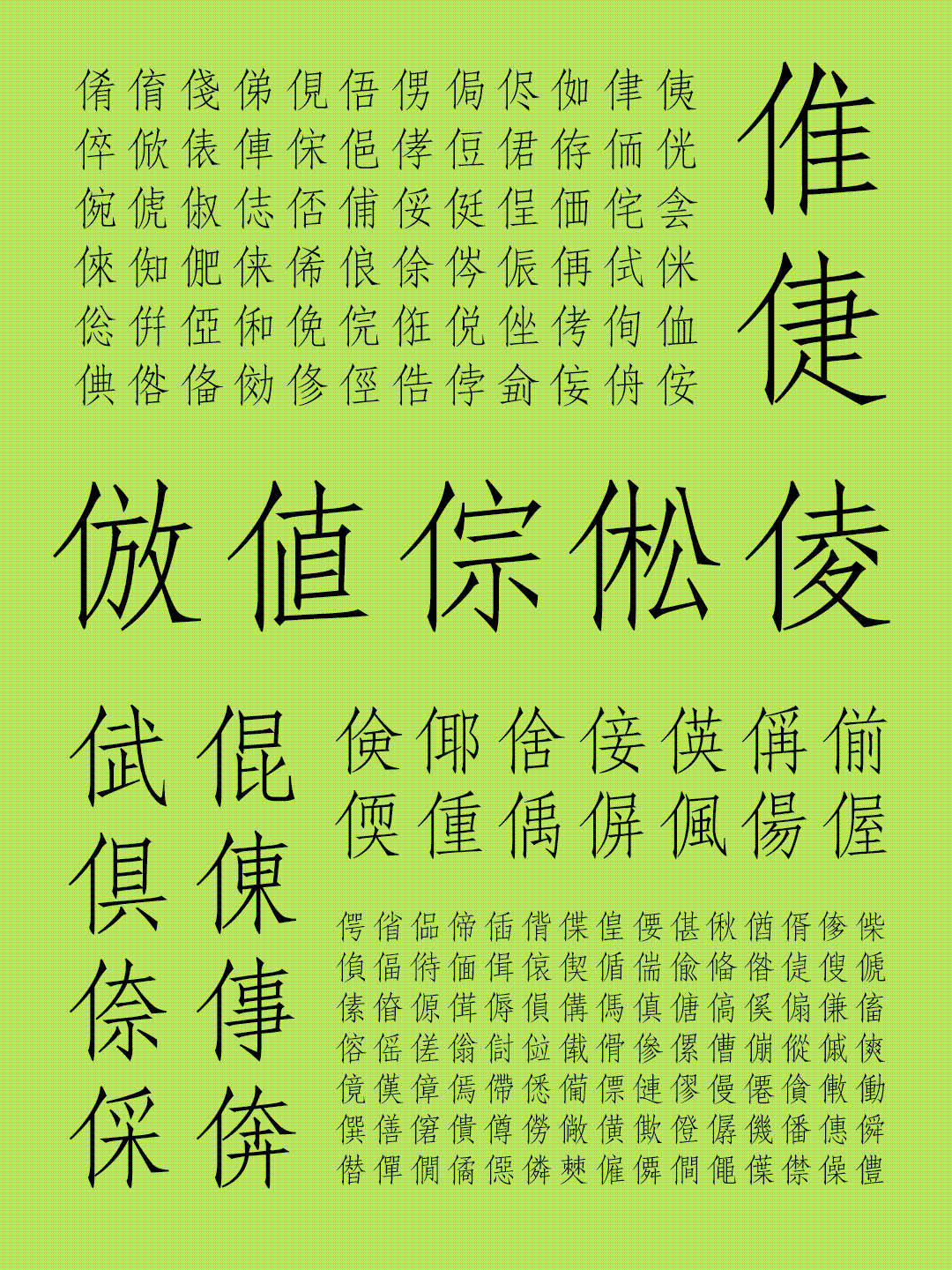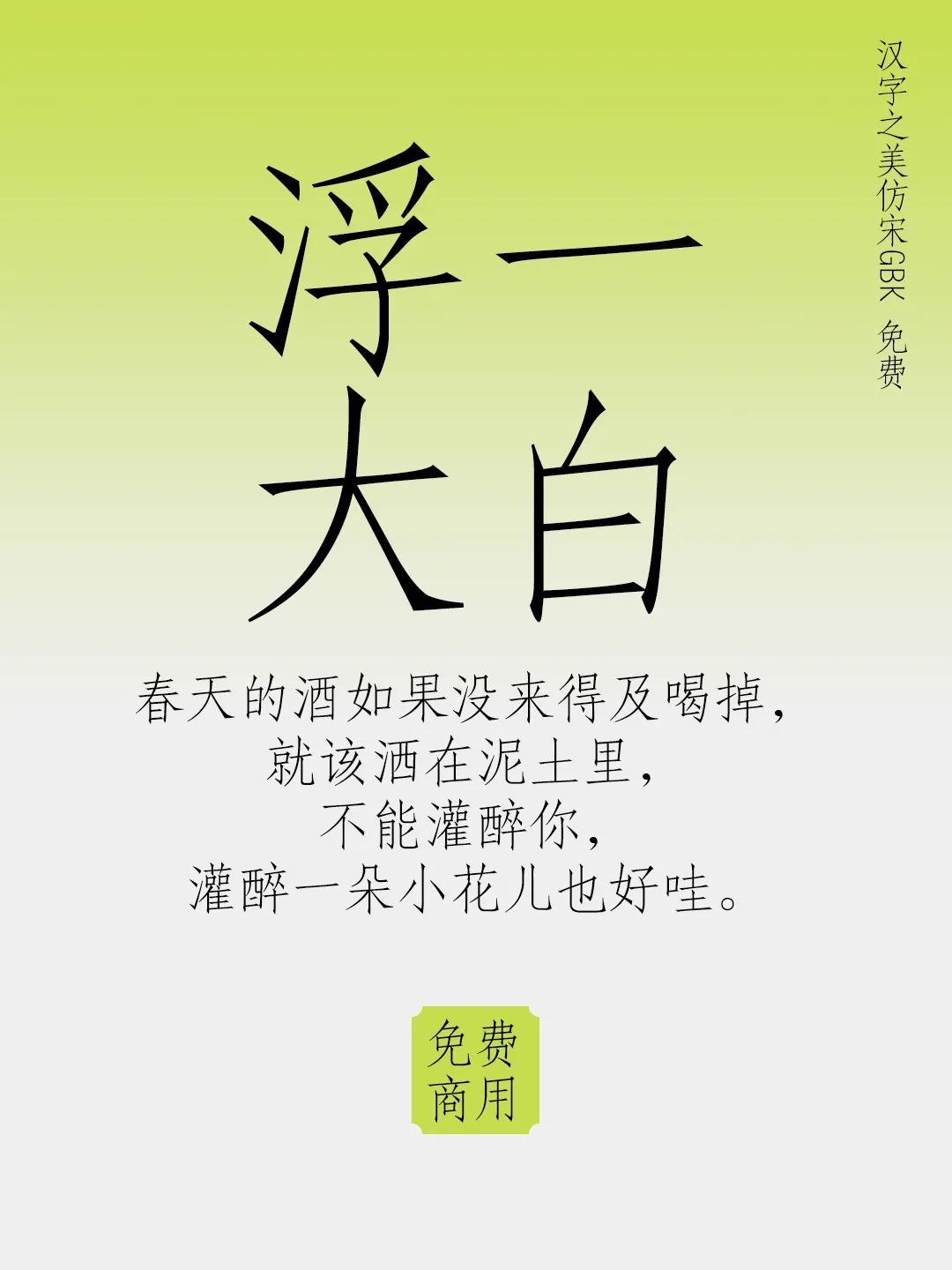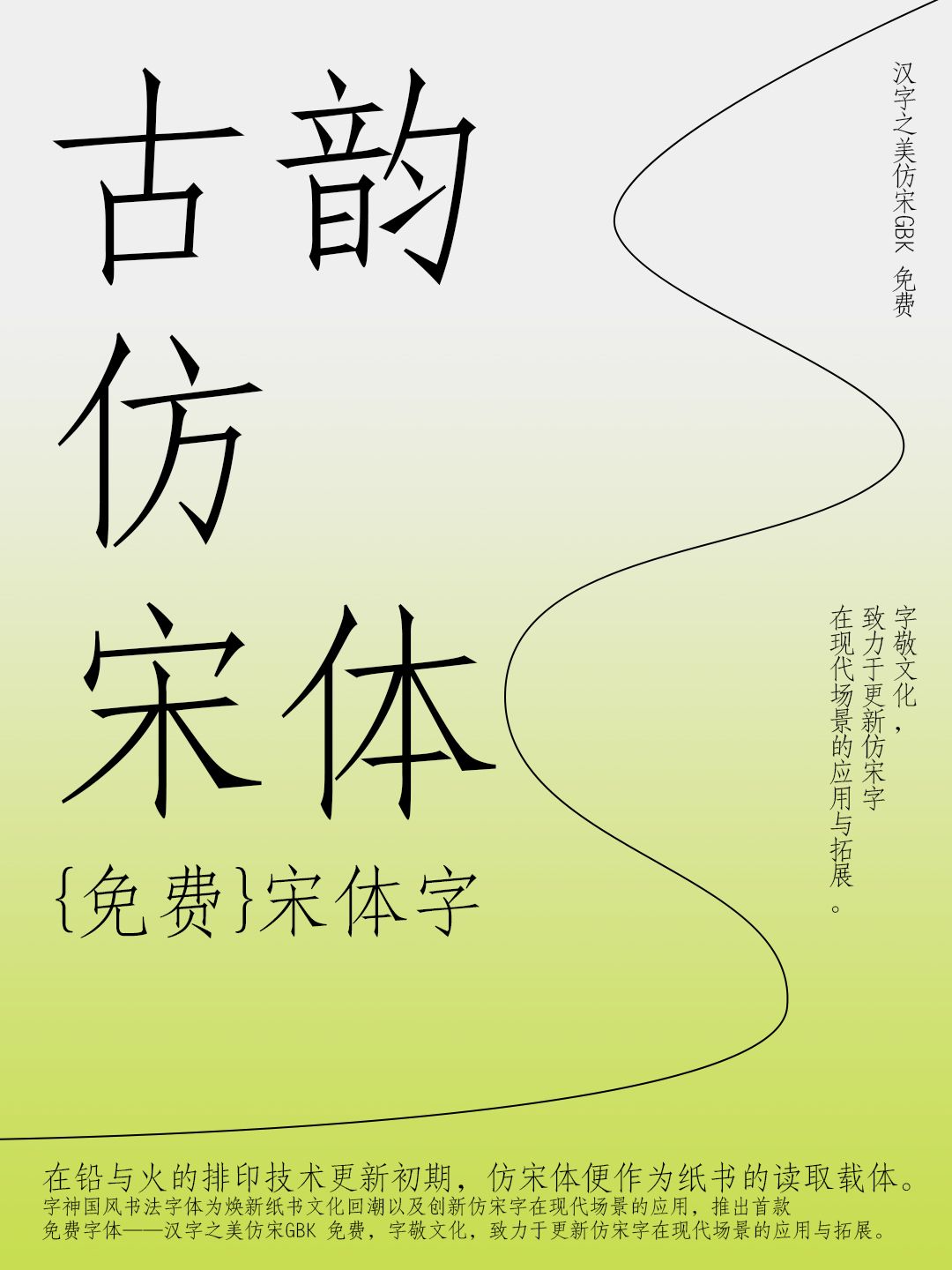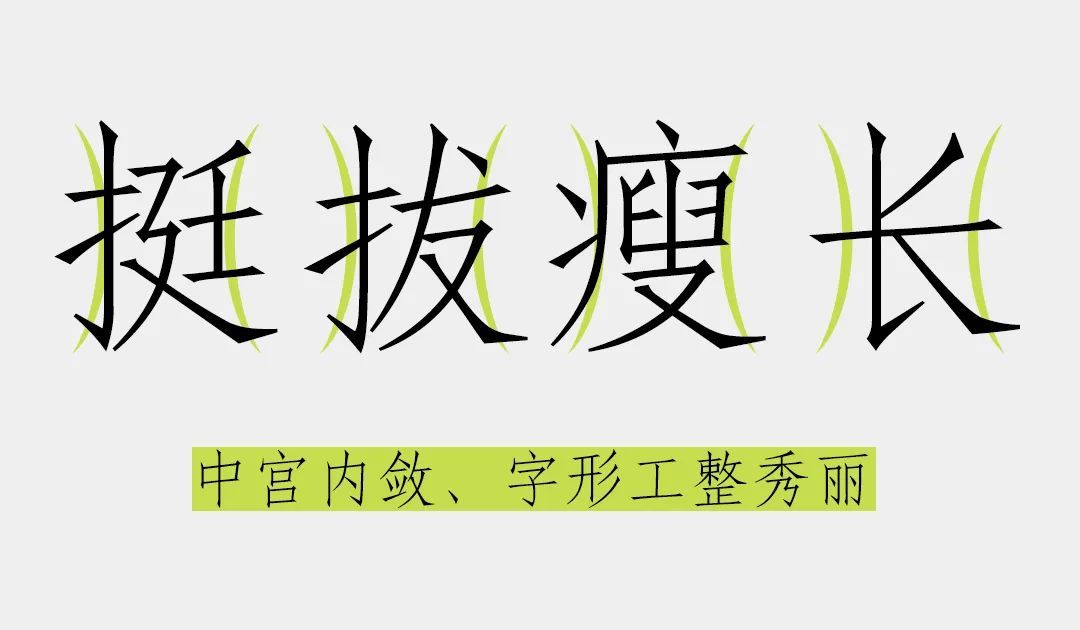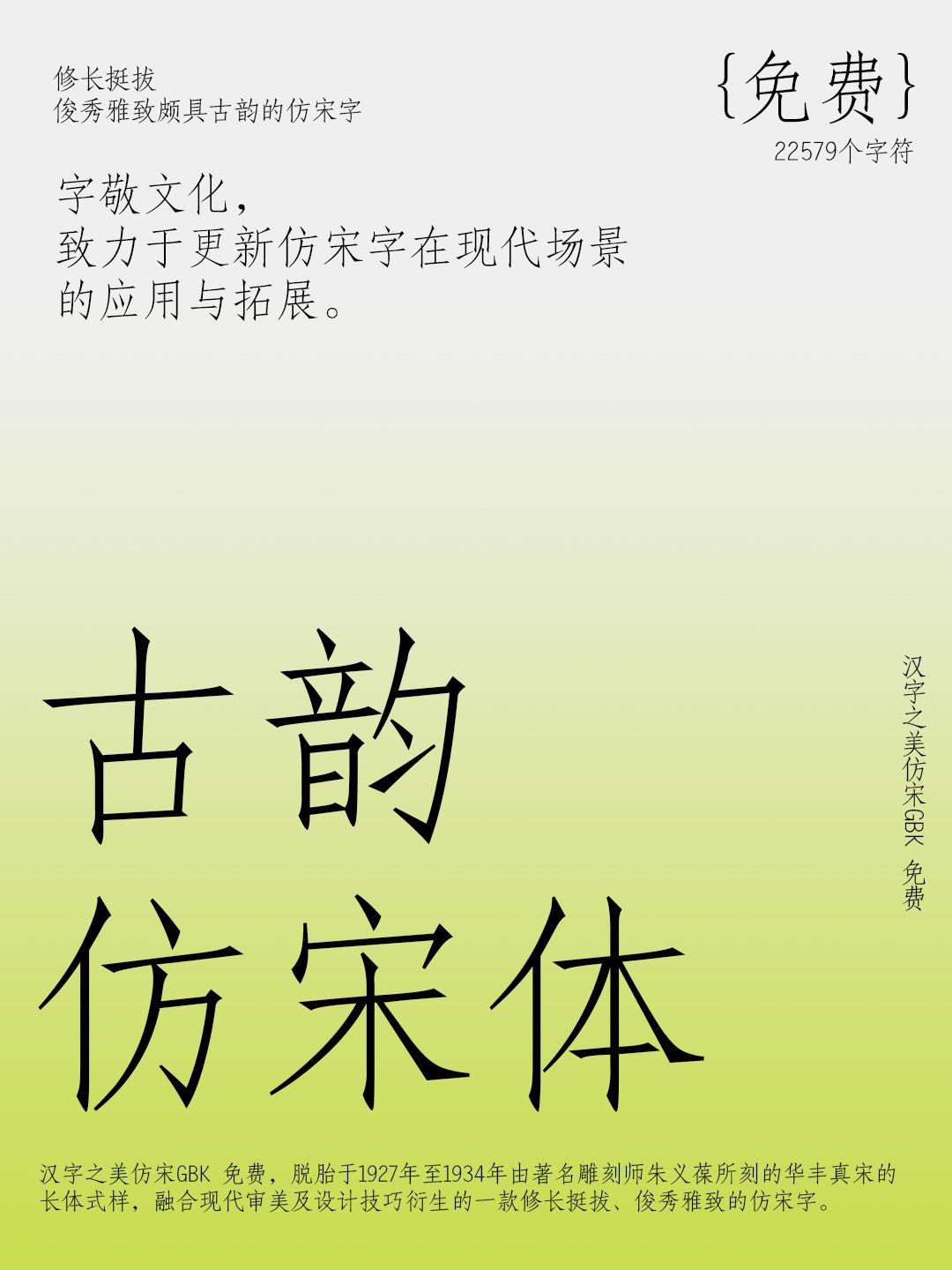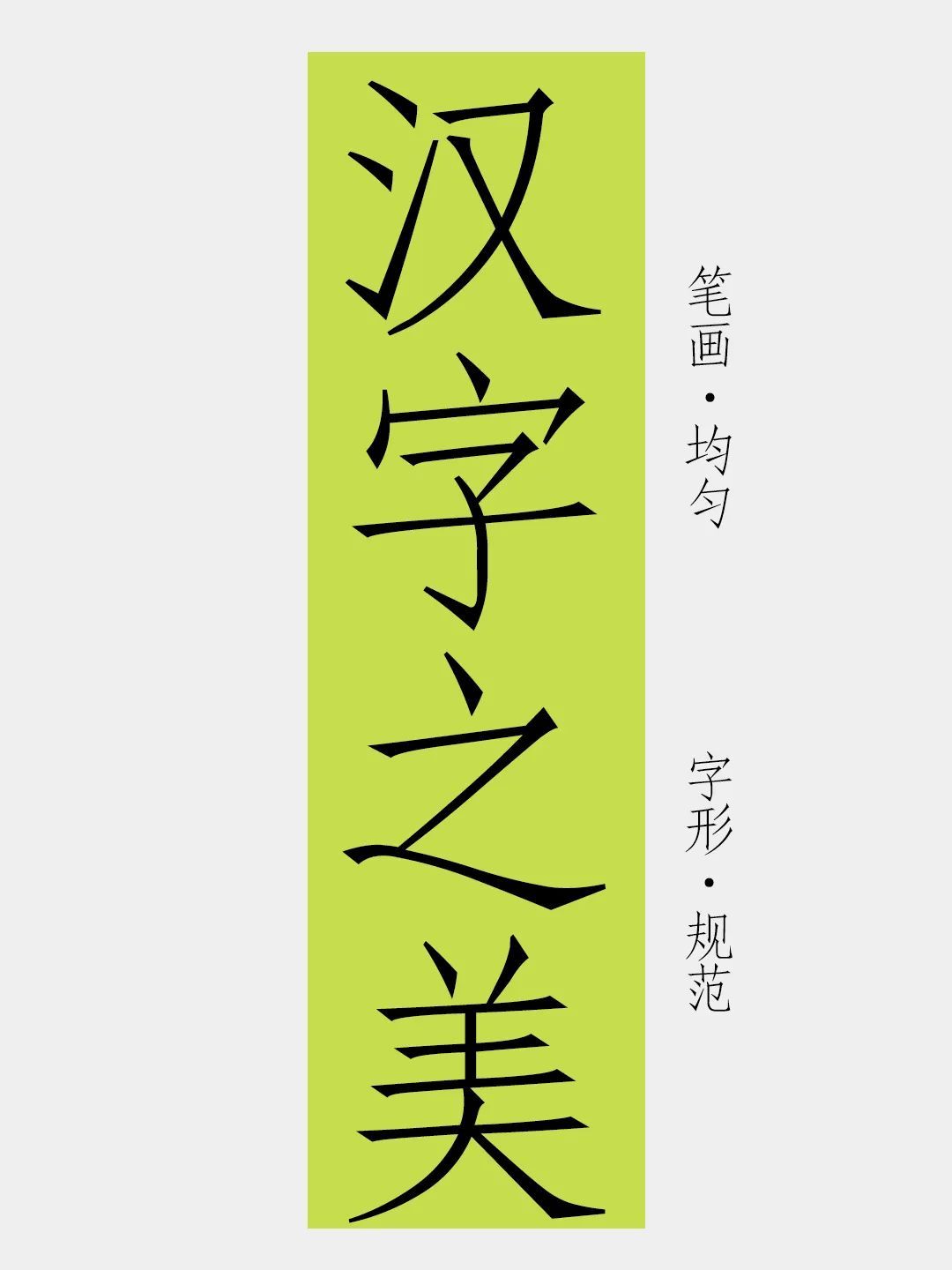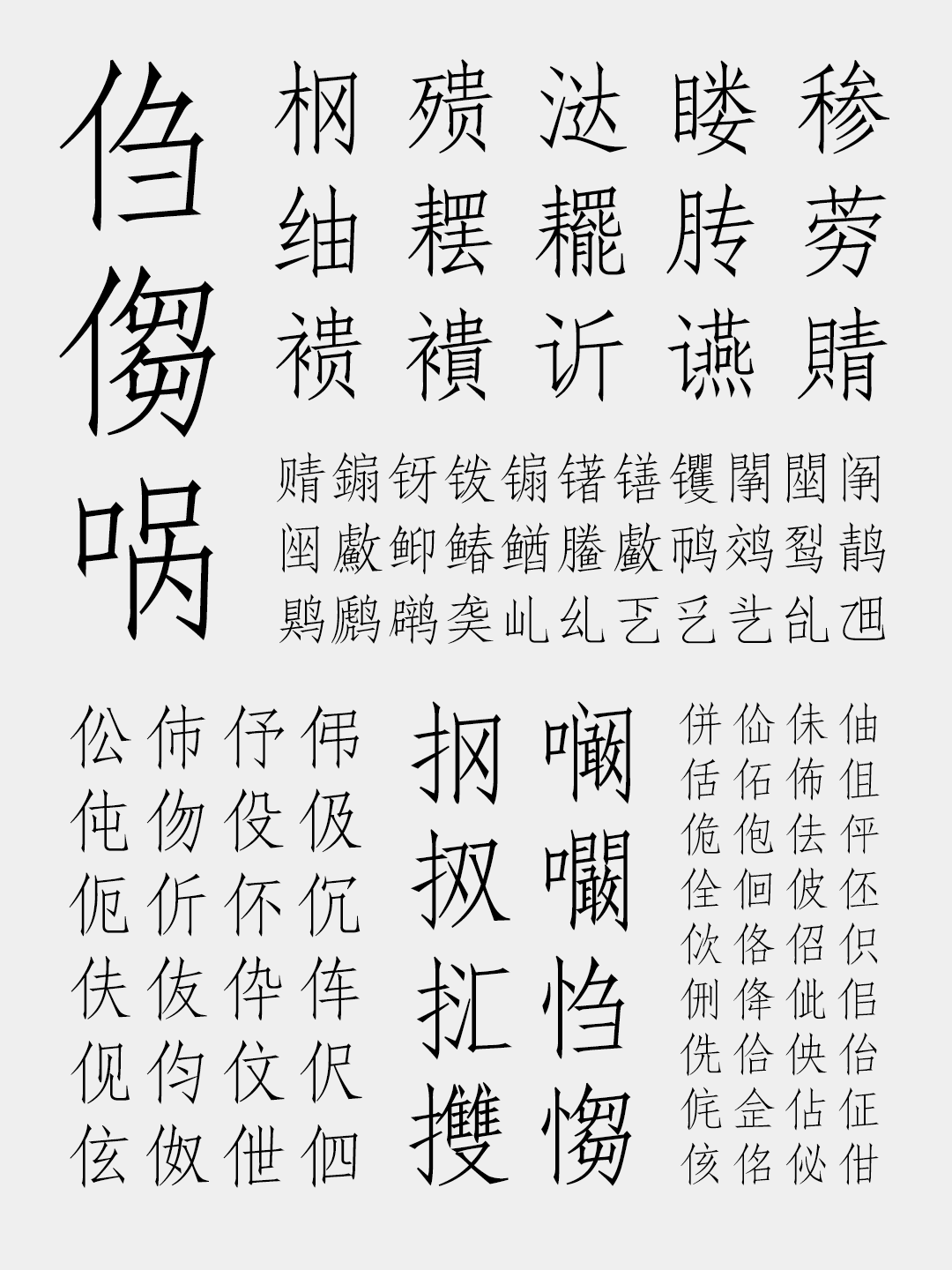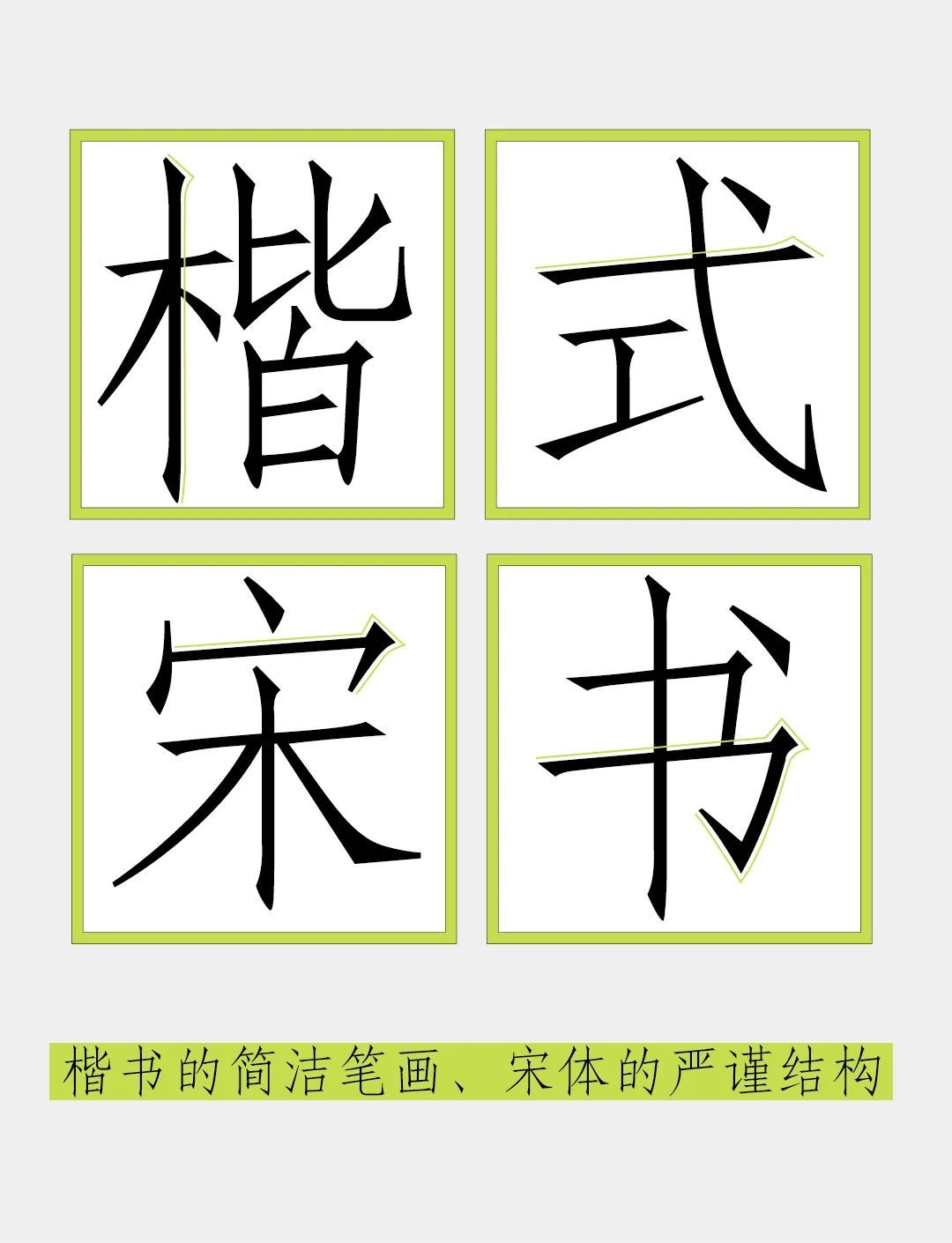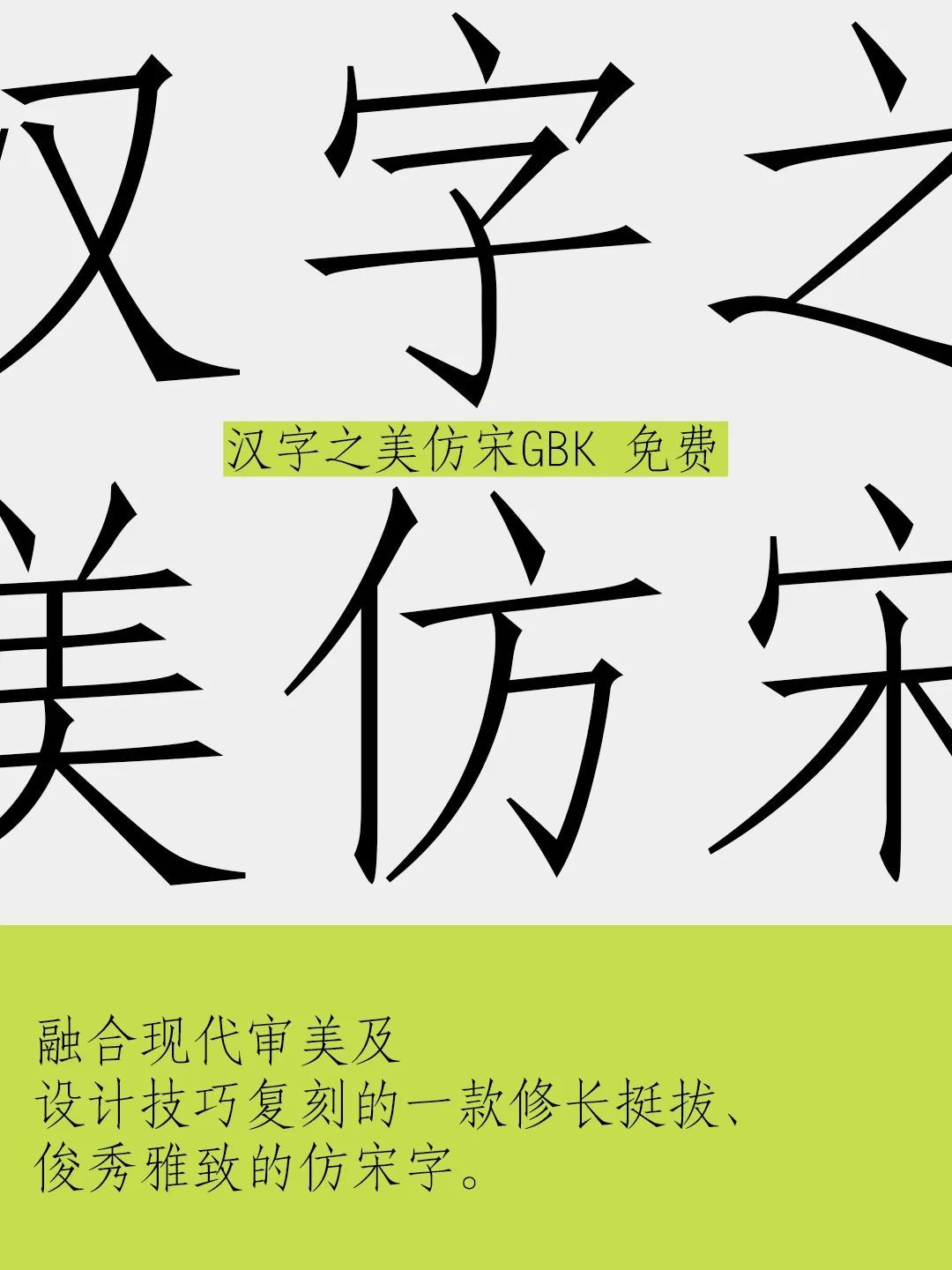
免费商用 | 汉字之美仿宋GBK 免费,22579大字符集助力现代用字
在屏显与数字像素为信息载体的当下,纸书的信息承载力正在衰减。铅活字印刷时期,仿宋体作为纸书印刷字体引领时代潮流。
字神国风书法字体为赓续纸书文化以及探索仿宋字的现代应用,推出首款免费商用字体——汉字之美仿宋GBK 免费,支持全场景(除软件内嵌与LOGO)免费商用,重现仿宋字独特的古韵美感与文化底蕴。
汉字之美仿宋GBK 免费,源于上海华丰铸模制造所的雕刻师朱义葆所刻的华丰真宋长体式样,融合现代审美及设计技巧复刻的一款修长挺拔、俊秀雅致的古韵仿宋字。
字型偏瘦长,结构规整统一,比例匀称,中宫内收。笔画灰度较小、粗细均匀,左低右高,明朗易读,规整的字型适配简洁明朗的版面效果。
笔画风格简约且带有明显的刻刀感,起、落笔呈倾斜状带有笔锋,楷书式简洁的笔画和宋版字体严谨的结构融合,出峰犀利,撇捺舒展,曲线流畅雅致而整体笔画具备力量感,刚柔相济。
汉字之美仿宋GBK 免费,共收录22579个字符,在国家规定的GBK编码标准上扩展近700个字符,涵盖屏显及古籍、辞海、生僻字、文档标准字等用字,减少冷僻字缺漏的情况。
助力多行业电子文件共享交流时以完美、准确、原版的显示效果,满足办公用字的需求。以其通用性、兼容性,支持多种输出设备和输出方式,诠释仿宋字在现代场景应用的魅力。
良好的可读性和可视性,也拓展了古韵字形在屏显时代的汉字美感与应用边界。整体视觉清晰美观,容易辨认,适用于正文排版、书籍、广告、媒体宣传等各种场景。
人工智能的科技浪潮下,纸书衍生为人文情感载体,仿宋字也在不同的应用载体中幻化出新的生命力。